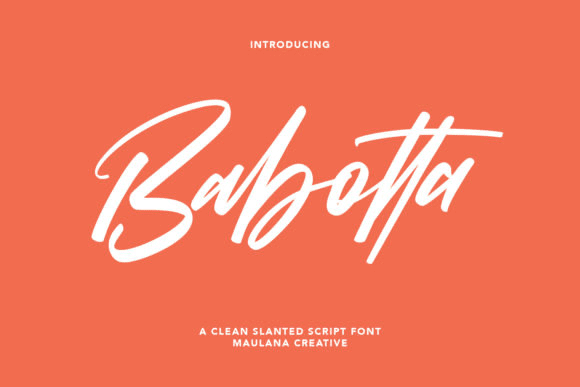
Название: Babotta Font
Бабота - чистый и современный шрифт.
Этот шрифт идеально подходит для всех ваших логотипов, брендинга, социальных сетей и хитрых DIY проектов.